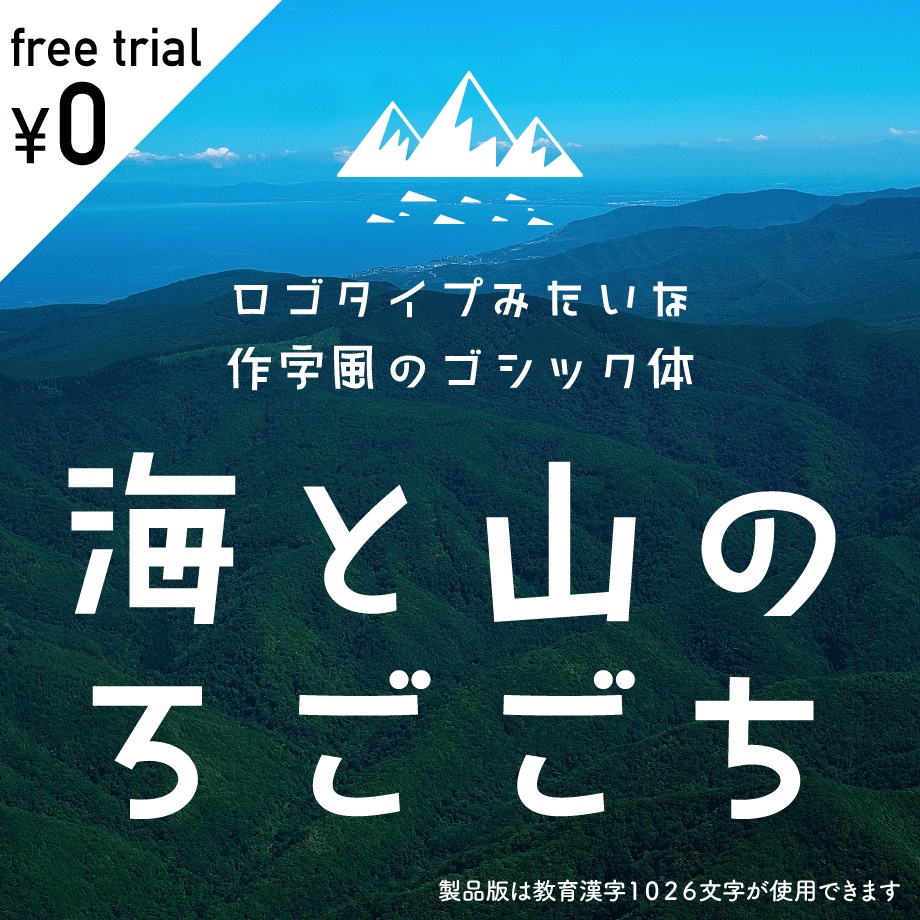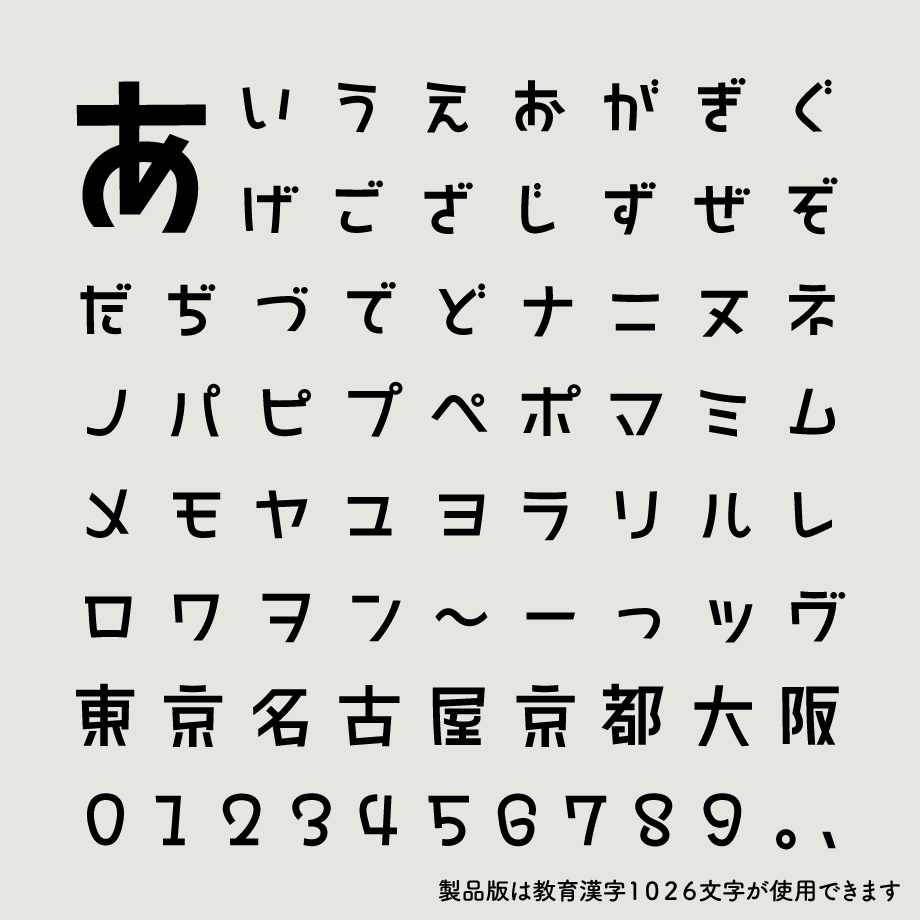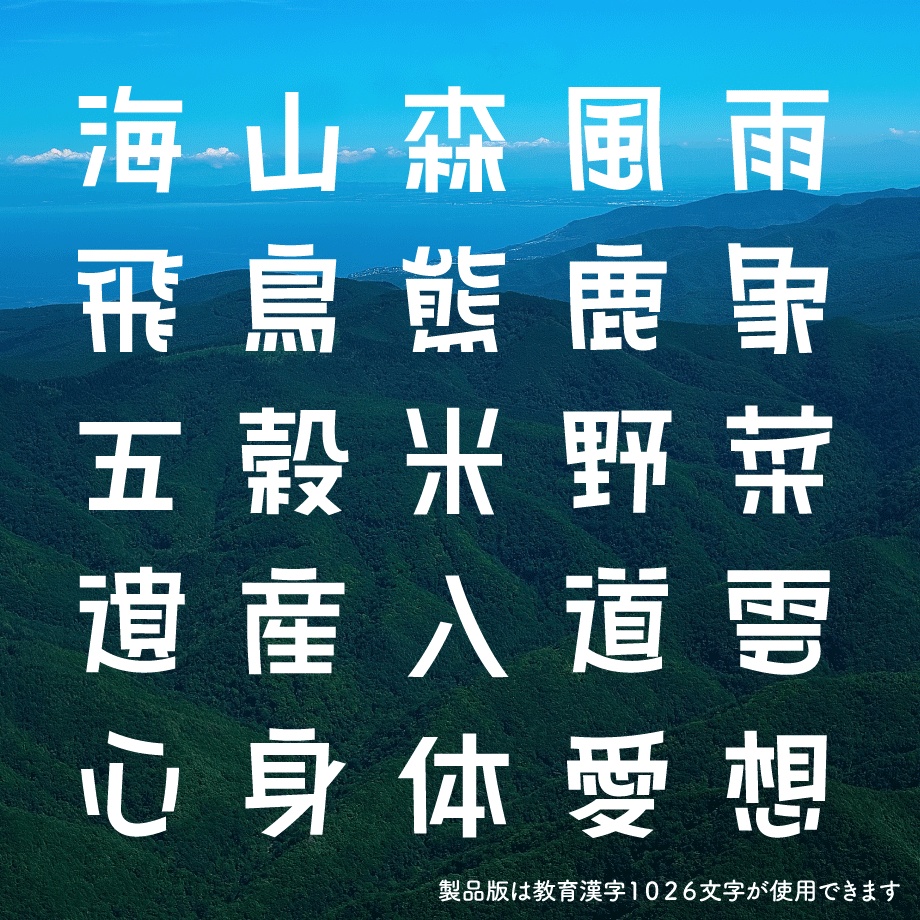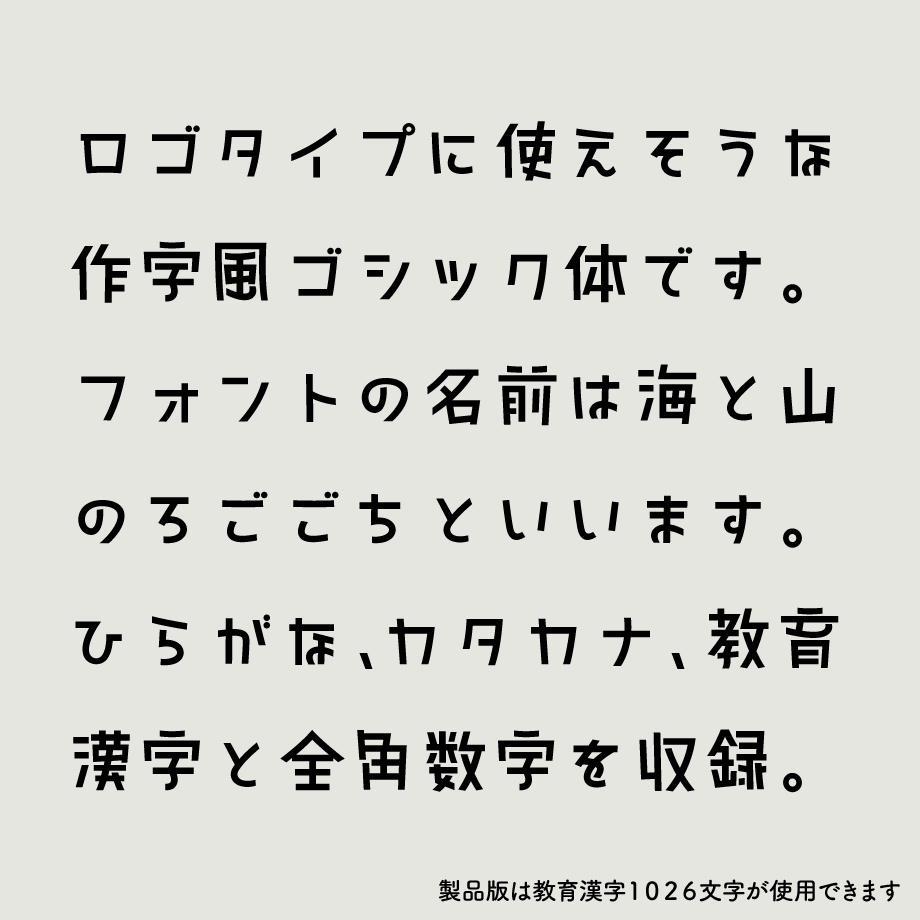
日本語フォント「海と山のろごごち」フリー版
日本語(和文)フォント「海と山のろごごち」は、ロゴタイプみたいな作字風ゴシック体をイメージしています。 ひらがなとカタカナ、漢字(海、山、体の3文字)を収録したお試し用の無料フォントデータです。 ● 仕様 フォントデータ形式:OpenType 収録字種:ひらがな・カタカナ・漢字3文字 「あいうえおかきくけこさしすせそたちつてとなにぬねのはひふへほまみむめもやゆよらりるれろわをんがぎぐげござじずぜぞだぢづでどばびぶべぼゔぱぴぷぺぽぁぃぅぇぉゃゅょっゎアイウエオカキクケコサシスセソタチツテトナニヌネノハヒフヘホマミムメモヤユヨラリルレロワヲンガギグゲゴザジズゼゾダヂヅデドバビブベボヴパピプペポァィゥェォャュョッヮヵヶー~海山体」 ● ダウンロード販売ご利用に際して ダウンロードされた本フォントデータは、お客様ご自身の責任においてご利用ください。 本フォントデータは、WindowsおよびMacにインストールすると、対応するグラフィックソフトやワープロソフトなどで利用可能となります。また、OSやソフトウエアおよびそのバージョンによっては読み込めないことがあります。フォントのインストール方法やソフトウエア上での使用方法の詳細は、各解説書などでご確認の上ご利用ください。 ● 免責事項 本フォントデータの使用または使用に関連して、購入者の直接または間接的に生ずる一切の損害および第三者からなされる請求について、タイピングアートは一切責任を負担しません。 ● 使用範囲 商用での使用は出来ません。 ● 禁止事項 本フォントデータはサーバー等にアップロードして送信可能とする目的の使用は出来ません。 本フォントデータの改変、販売、頒布、バックアップ目的以外のコピーは許可されていません。 本フォントデータを使用して作成した成果物の著作権登録、意匠登録および商標登録など知的財産権の登録を行うことは許可されていません。